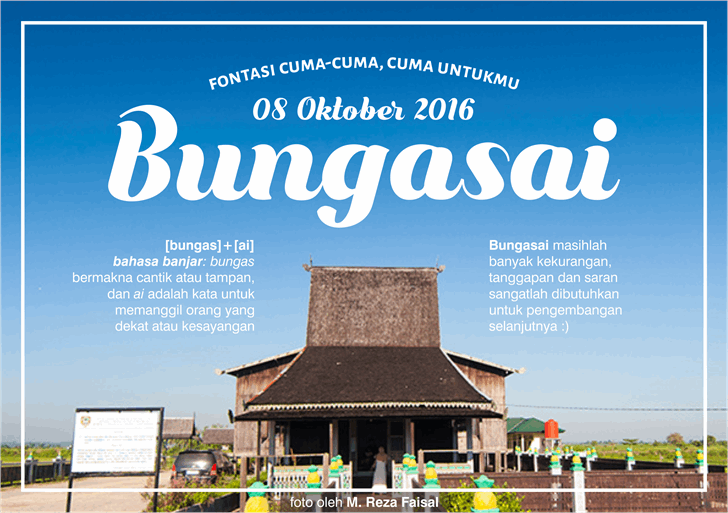
Bungasai Font – Fonte Grátis
Bungasai Font
A Bungasai é uma fonte Display que surge diretamente do idioma Banjar, sendo derivada das palavras “bungas+ai”, usadas para elogiar alguém bonito ou atraente (uma forma de elogio). Essa descoberta fez com que Gunarta criasse sua primeira fonte em um longo período, se compararmos à versatilidade dos seus projetos mais recentes. A Bungasai não é apenas uma ferramenta visual; ela carrega consigo a história de quem está por trás dela. Seja por suas origens culturais ou pelo esforço que foi necessário para criar, esta fonte mantém uma essência única e fascinante. Essa singularidade torna-a não apenas uma escolha estética, mas também uma maneira de expressar a diversidade cultural do Brasil através dos recursos gráficos digitais.